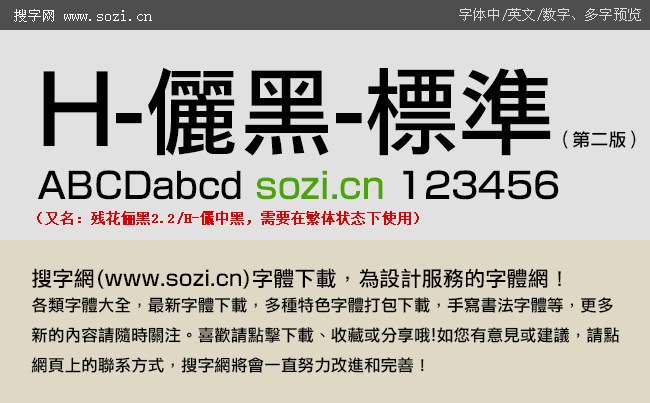
殘花儷黑2.2-標(biāo)準(zhǔn)
搜字網(wǎng)提供一款殘花儷黑2.2-標(biāo)準(zhǔn)中文字體下載,殘花儷黑2.2-標(biāo)準(zhǔn)是一款非常端正的黑體字體,字體端正大方,簡(jiǎn)潔易讀,適合廣告設(shè)計(jì)、畫冊(cè)排版、包裝設(shè)計(jì)等設(shè)計(jì)場(chǎng)合使用。